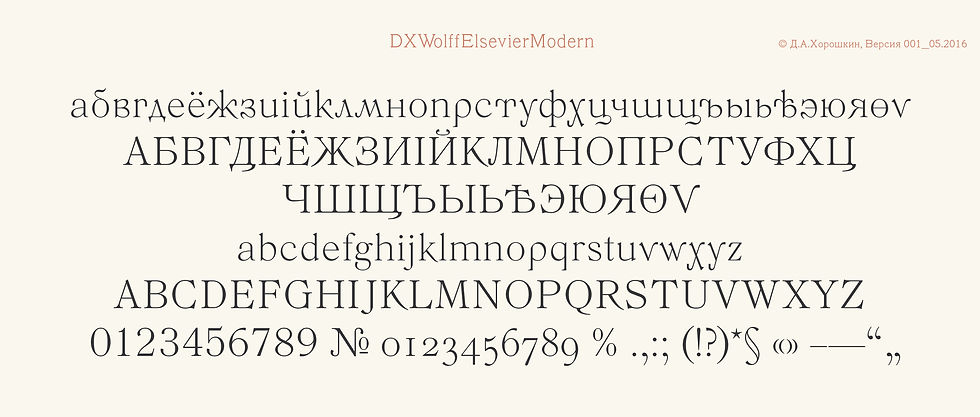
Шрифт DXWolffElsevierModern10 мая 2016 г.1 мин. чтенияВыпущена цифровая версия дополнительного начертания Modern к шрифту Эльзевир, словолитни М.О.Вольфа. #старинный #Вольф #дореволюционный #Эльзевир #шрифт #DXWolffElsevier #DXWolffElsevierModern